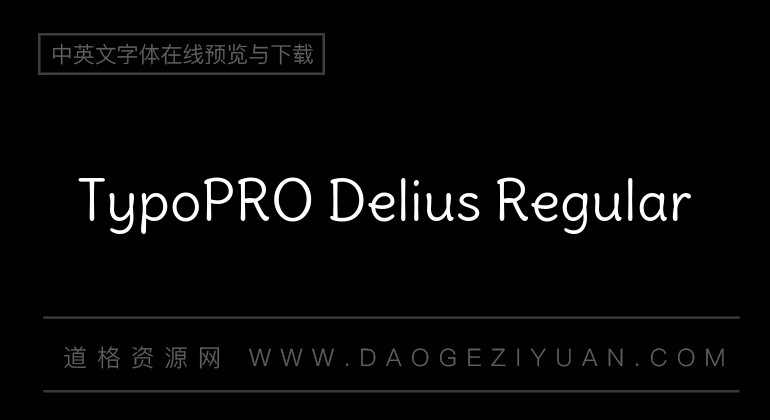
TypoPRO Delius Regular字体是一种优美的手写风格字体,其字形略带圆润,线条流畅自然,呈现出一种亲切、温暖的感觉。该字体适用于多种场合,如印刷、广告、包装设计、网页设计等等,能够为设计带来独特的风格和视觉效果。此外,该字体还支持多种语言,使得它可以在全球范围内广泛使用。总的来说,TypoPRO Delius Regular字体是一种非常优秀的字体,可以为各种设计项目增添特色和美感。文件名:TypoPRO-Delius-Regular-2.ttf
TypoPRO Delius Regular是一款非常不错的手写艺术字体,具有很好的视觉感,适合于文化类的宣传设计、商业类品牌的广告和产品包装设计以及个性化文字排版等较多场景。